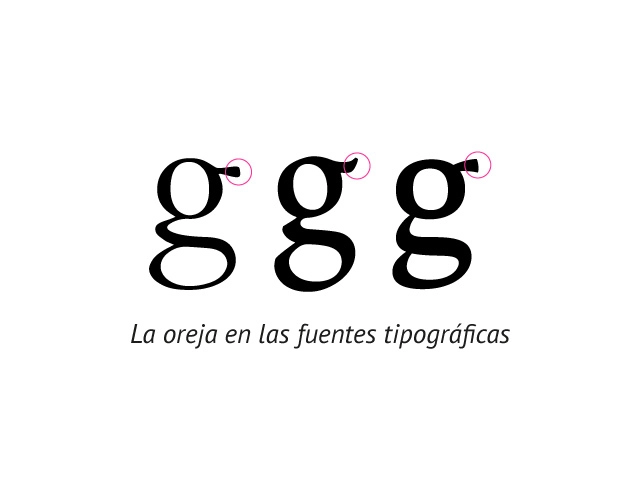
OREJA
En algunas fuentes tipográficas, es la parte de la letra en forma de pequeño rasgo lateral que sale por el lado superior derecho de la letra g minúscula.